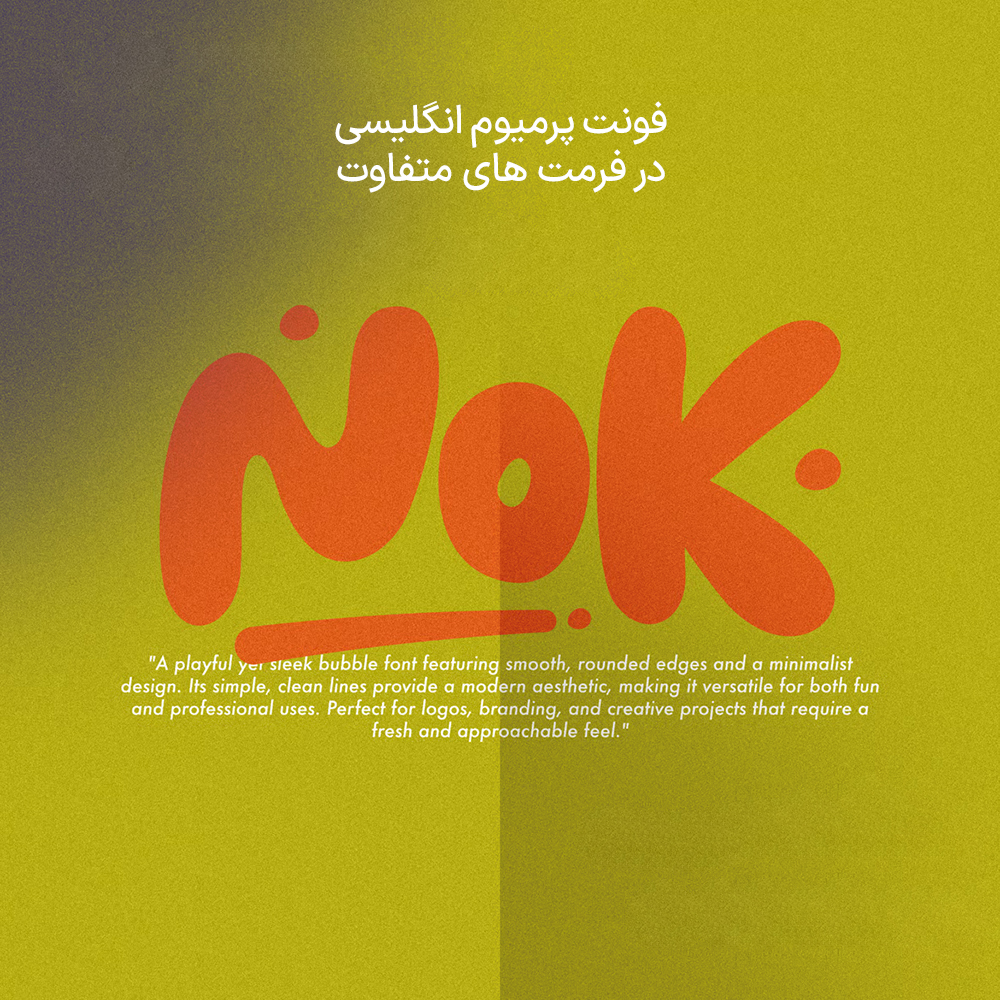
فونت پرمیوم و انگلیسی Nok Font یک فونت جدید و تازه که با سادگی، تمیزی و پیچشی مدرن در سبک حباب کلاسیک طراحی شده است. این فونت دارای لبههای گرد و منحنیهای نرم است که به هر طرحی جلوهای بازیگوشانه و در عین حال پیچیده میبخشد. Nok که برای لوگوها، تیترها، پوسترها یا هر پروژه خلاقانهای که ظاهری دوستانه و امروزی را میطلبد، ایدهآل است، خوانایی آسان را با شخصیتی منحصر به فرد ترکیب میکند.